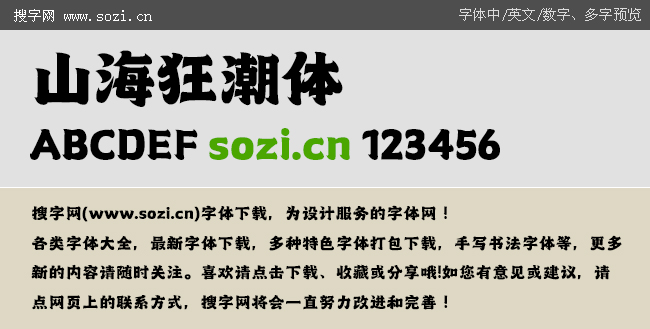
山海狂潮體
搜字網(wǎng)提供一款山?癯斌w中文字體下載,山?癯斌w字體是一款手寫(xiě)風(fēng)格的毛筆字體。山?癯斌w字體粗壯有力,字形端莊大氣,視覺(jué)效果非常不錯(cuò)。適合標(biāo)題設(shè)計(jì)、海報(bào)設(shè)計(jì)、廣告設(shè)計(jì)等應(yīng)用。